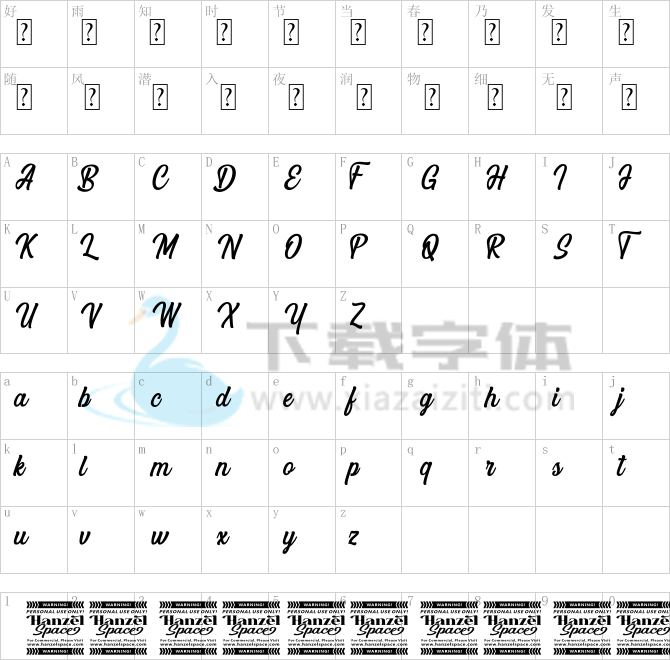
Angler Letter.otf字体下载,这款字体结构工整、笔画清晰,兼顾美观与易读性,适用于标题、正文、海报、包装、LOGO 等多种场景。字形优雅稳定,风格百搭耐看,适配日常排版与创意设计,让文字呈现更舒适、更具质感。Angler Letter.otf字体下载一笔一画,皆是细节,以均衡的比例、流畅的线条打造舒适视觉体验,字形端正大气,风格简约现代。无论是商业设计、品牌宣传还是日常排版,都能轻松驾驭,让文字更有格调与力量。Angler Letter.otf字体下载字体下载。